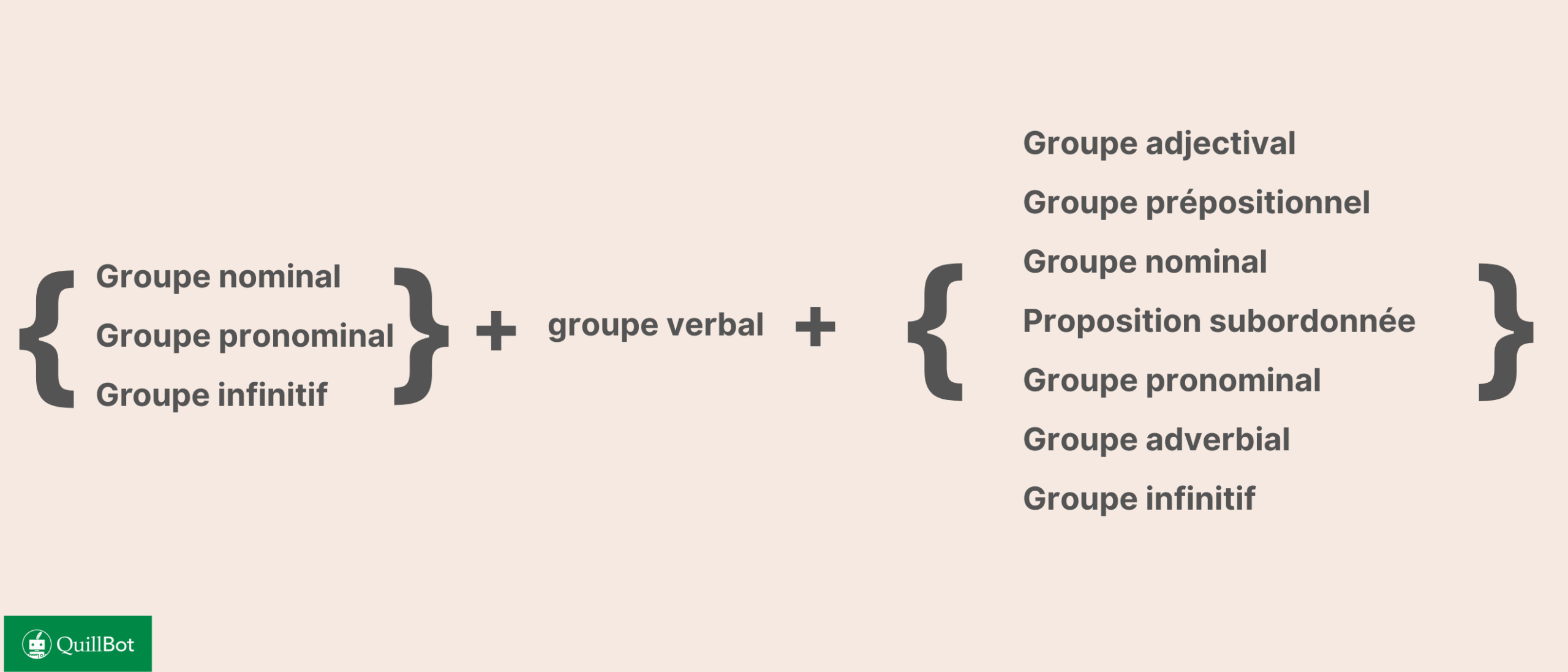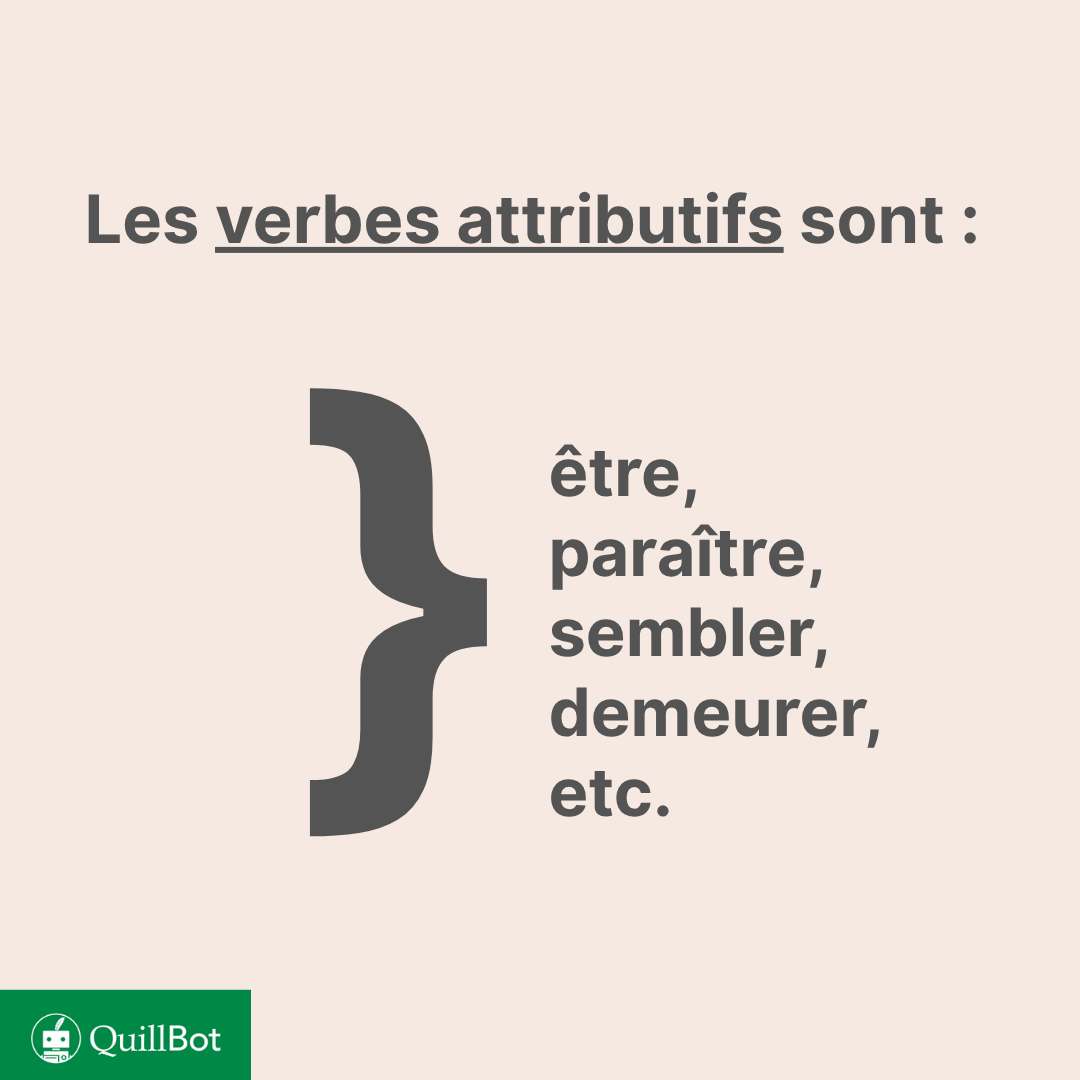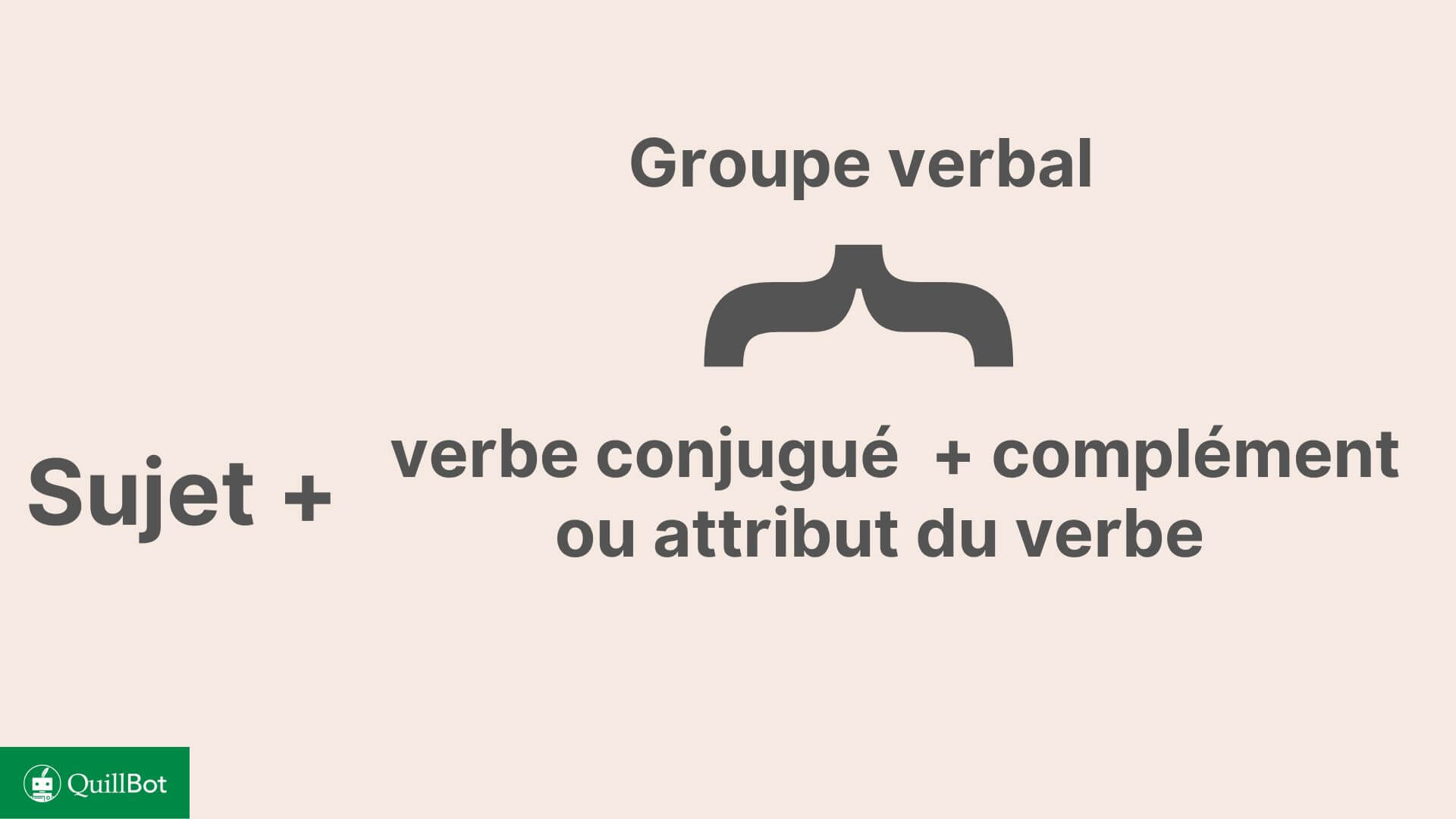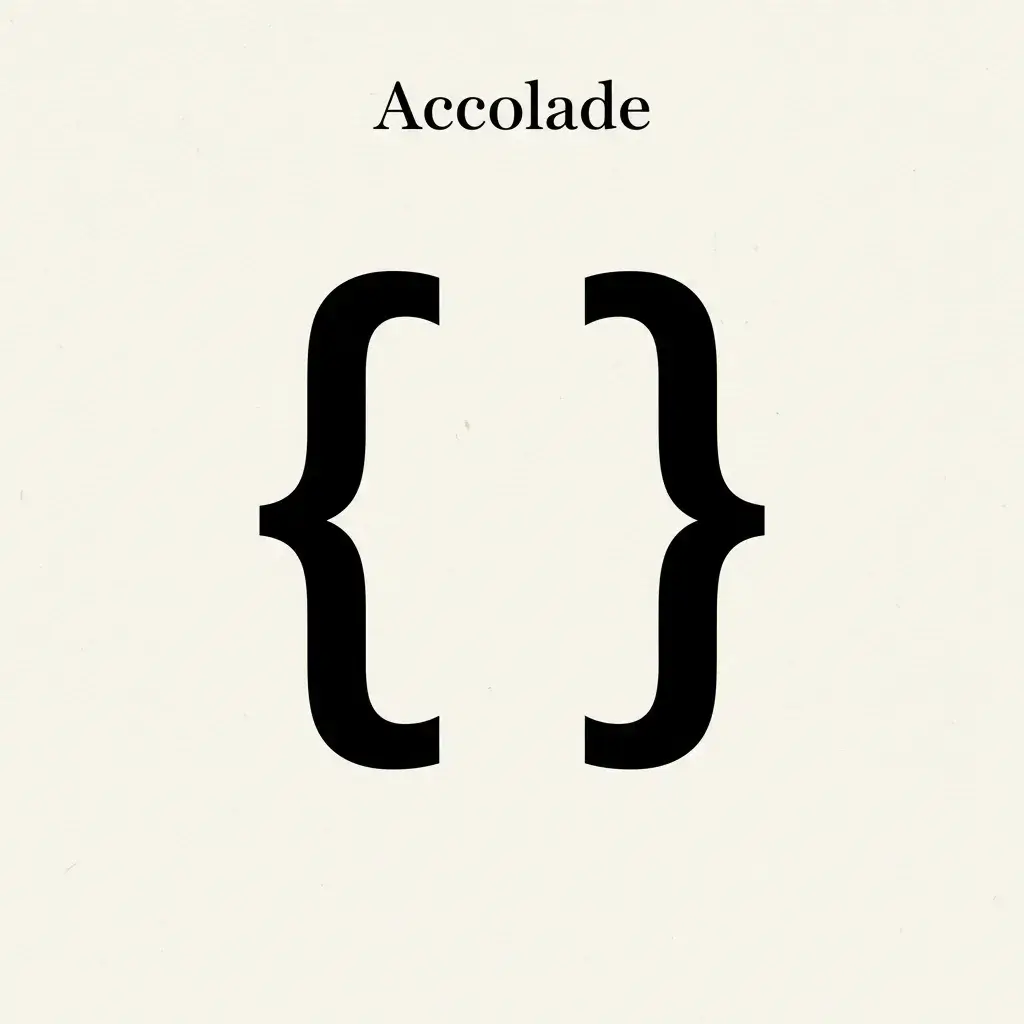
Accolade | Emploi et origine
L’accolade ( { } ) est un signe typographique formé d’une double courbure. Qu’elle soit ouvrante ou fermante, l’accolade sert à lier plusieurs éléments.
Seul signe double à ne pas être obligatoirement utilisé en paire, elle peut se placer à la verticale comme à l’horizontale.
Musicienne, architecte, diplomate et invariablement rassembleuse, l’accolade affiche fièrement son étymologie jusque dans sa forme.
Et le moins que l’on puisse dire, c’est que, sous son faux air de moustache, elle nous en bouche un coin…
L’accolade : signe typographique
L’accolade s’emploie seule ou en paire, à la verticale ou à l’horizontale, pour rassembler différents éléments qui se situent en dessous ou à côté les uns des autres.
Bien que l’accolade nécessite une certaine maitrise graphique, son symbole peut tout à fait s’insérer dans un document numérique.
Accolade symbole
L’accolade verticale utilisée seule réunit des éléments placés sur différentes lignes. En musique, elle commence d’ailleurs la portée pour en réunir les cinq lignes parallèles.
accolade typographie
Utilisées en paires, les accolades verticales ne se contentent pas de regrouper des éléments, elles les isolent des autres.
L’accolade peut également s’utiliser à l’horizontale pour rassembler et isoler des éléments placés dans des colonnes.
Là encore, la notion s’exporte en dehors du domaine langagier. En architecture, un arc en accolade est formé de deux courbes successivement convexes et concaves. De forme horizontale, elle est posée sur le tronc, la partie verticale de la colonne d’un édifice.
L’accolade, qu’elle soit unique ou double, verticale ou horizontale, est un des rares signes typographiques à être majoritairement manuscrit. Elle est généralement dessinée par le scripteur pour expliciter rapidement et lisiblement les liens d’appartenance entre différents éléments.
Si elle peuple les tableaux des salles de cours et les notes des étudiants, c’est parce que son trait caractéristique rassemble et lie. Et cette symbolique est loin d’être le fruit du hasard…
L’accolade : origine
En tant que terme, l’accolade est utilisée dans les domaines de la musique et de l’architecture. En tant que mot, l’accolade possède plusieurs sens, et sa polysémie relève presque de l’évidence.
En plus d’être un signe typographique, l’accolade est une action, celle de serrer physiquement quelqu’un dans ses bras. Ce geste est surtout une des rares marques d’affection tolérée entre deux hommes, au-delà des codes sociaux et religieux.
Chaleureuse, fraternelle, l’accolade possède une véritable portée diplomatique lorsqu’elle a lieu entre deux chefs d’État. Plus qu’une poignée de main, elle prend même la forme d’une véritable embrassade entre les joueurs d’une équipe sportive.
Au Moyen Âge, un jeune noble devenait chevalier lors de l’adoubement, une cérémonie au cours de laquelle il recevait son titre et son arme. Le cérémonial impliquait que le Roi passe les bras autour du cou du futur chevalier.
Pratiquée dans toute l’Europe médiévale, cette tradition féodale est aussi désignée par le mot accolade en anglais. Mieux encore, le signe typographique se traduit par opening or closing brace pour accolade ouvrante ou fermante.
Le mot anglais brace, que l’on retrouve dans embrace (étreinte, embrassade) vient du latin bracchia, lui-même pluriel de bracchium, signifiant « bras ». Autrement dit, brace désigne une action réalisée avec les deux bras. Le mot français accolade, lui, vient aussi du latin, mais de collum, qui signifie « cou ».